「韓国語のスローガン」にぴったりな韓国語フリーフォント
今回の記事は、K-POPや韓流アイドルを応援する推し活グッズ「スローガン」を作るときにぴったりな韓国語(ハングル)のフリーフォントをご紹介します!
韓国や日本国内でもライブが行われていますが、そんなときに推し活グッズ「スローガン」を作るファンも多いかと思います。
そのような場面で使える「スローガン」が目立つフォント選びができるようなフォントをまとめています。グッズ制作で人気あるフォントや、韓国国内のテレビ番組やYoutuberの方が利用している定番フォントなどもあるので、ぜひ参考にしてみてください。
韓国語の「スローガン」で使えるフリーフォント
以下のサンプルは、本記事で紹介していている韓国フリーフォントの1部ですが、韓国フォントも多種多様で見ているだけでも楽しいですね。ぜひ、自分にぴったりなフォントを見つけてみてくてださいね。
사물함【極太系】
シンプルな文字ですが、文字先に少しだけトゲのような装飾デザインが付いているフォントです。このちょっとした装飾がアクセントになっている可愛らしいデザインです。
모야모야【極太ゴシック/シンプル】
ハングル文字の中の「0」などの中窓が『/(スラッシュ)』のような形でくり抜かれているシンプルながらちょっと個性的なフォントです。
평창평화체【極太ゴシック/装飾デザイン】
文字に星のイラストが埋め込まれているのが、とても可愛らしいフォントです。韓国国内のYoutube動画やサムネイルで人気のあるフォントです。
K-POPを中心に流行っているY2Kにぴったりなので、「スローガン」グッズ制作に向いているフォントです。
고령딸기체【装飾デザイン/手書き】
光沢のようなデザイン模様がついているのが特徴的なデザイン。感情的な言葉を込めた「スローガン」を作るにはぴったりなフォントです。
Gasoek One【極太ゴシック系】
シンプルな超極太ゴシックフォントです。ドーンと目立つ文字なので、ライブ・コンサートに持っていく推し活グッズ制作するなら、こちらのフォントがおすすめです!
창원단감아삭체【極太/ゴシック系】
視認性ギリギリまで太めにしているので、非常にインパクトもあるフォントです。極太フォントゆえの可愛さも感じるハングルフォントです。
とっても目立つので、ライブに持っていくスローガンや推し活グッズ制作するなら、おすすめです!
CAFE24 PRO UP【極太/ゴシック系】
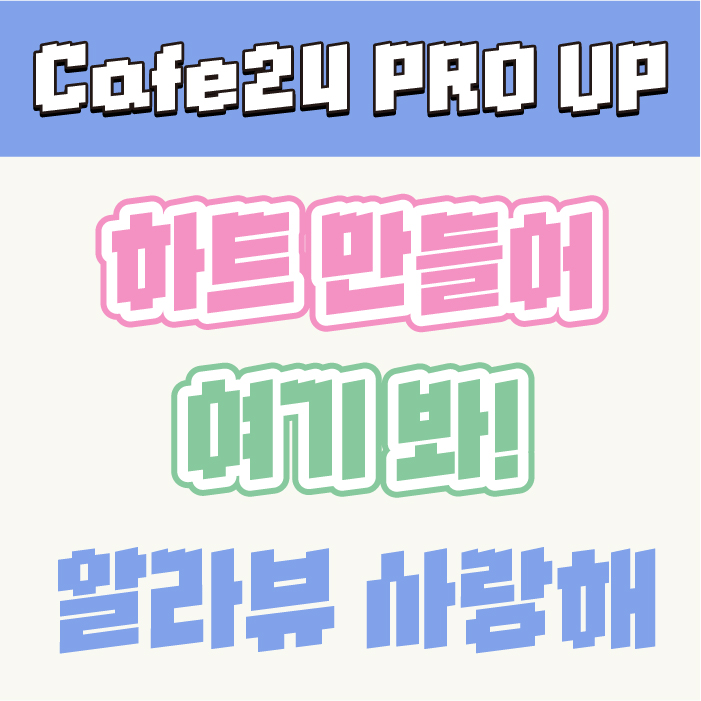
文字の上辺がデコボコとしたデザインが特徴的なゲームっぽさのあるハングルフォントです。
Y2Kやゲームのような世界観にぴったりなデザインフォントです。
파셜산스【極太/ゴシック系】
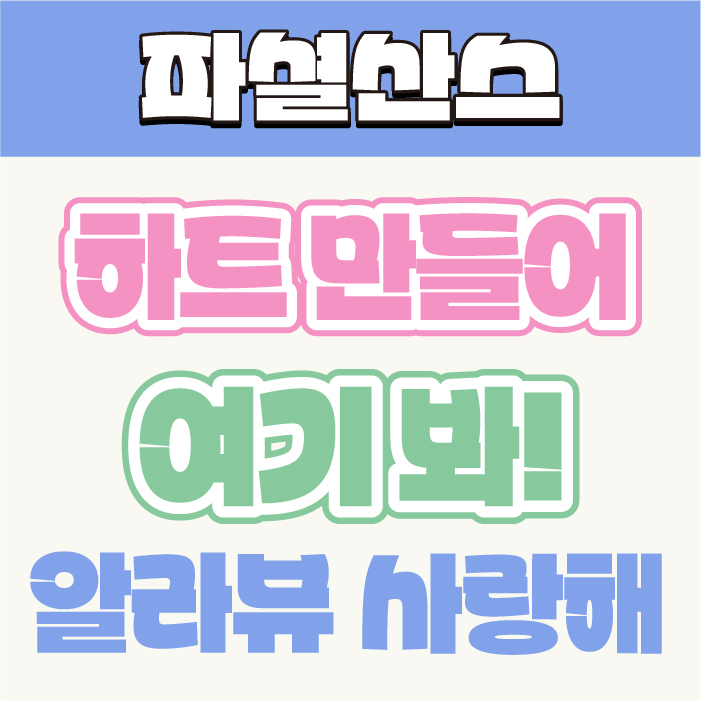
丸みがとっても可愛らしいハングルフォントです。日本語で言うポップ体のような雰囲気があるフォントです。
極太で目立つので、スローガンや推し活グッズ制作するなら、おすすめです!
땅스부대찌개【シンプル/丸ゴシック系】
日本語「丸ゴシックやフォーク体」のスタイルをもつ、丸みがあるフォルムが可愛らしいフォントです。
태백체【シンプル/ゴシック系】
日本語でいう「ゴシック体」のベーシックなフォントです。汎用的に幅広い場面で使えるフォントなので、とっても使いやすいかと思います。
국민연금체【シンプル/丸ゴシック系】
こちらはベーシックな丸ゴシック系です。曲線と角丸の具合が良いバランス感で使いやすい韓国語の丸ゴシックです。シンプルな丸文字韓国語フォントを探しているなら、こちらがおすすめです。
Bagel Fat One【極太/装飾デザイン】
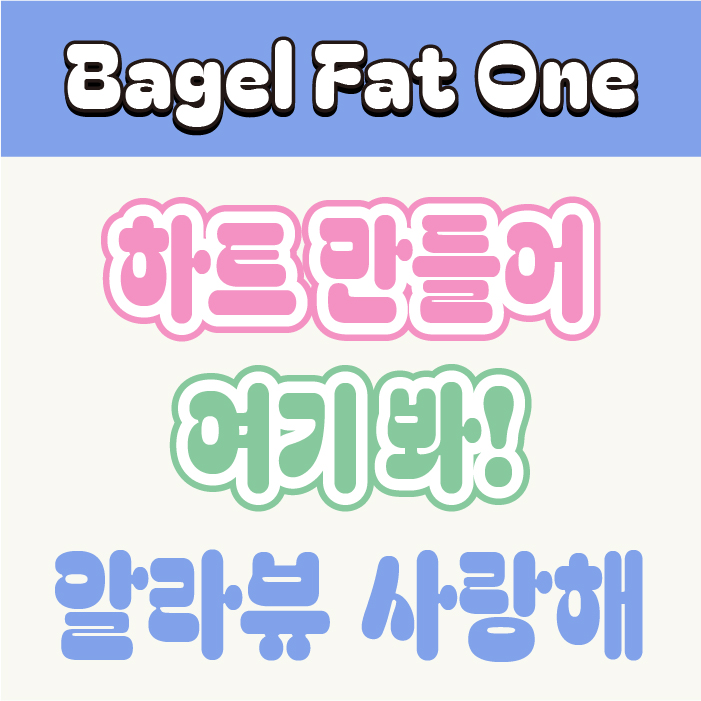
韓国国内のYoutube動画のテロップやサムネイルで人気のあるフォントです。
日本語フォントでは、見かけないスタイルのデザインなので、目立つこと間違いないフォントなので、「スローガン」におすすめ!
코트라 희망체【手書き文字】
サインペンやマジックのような太めのペンで書いた手書き韓国語フォントです。本記事で紹介しているフォントのなかでは、一番細いウェイトのフォントなので、長文のメッセージなどに向いているフォントです。